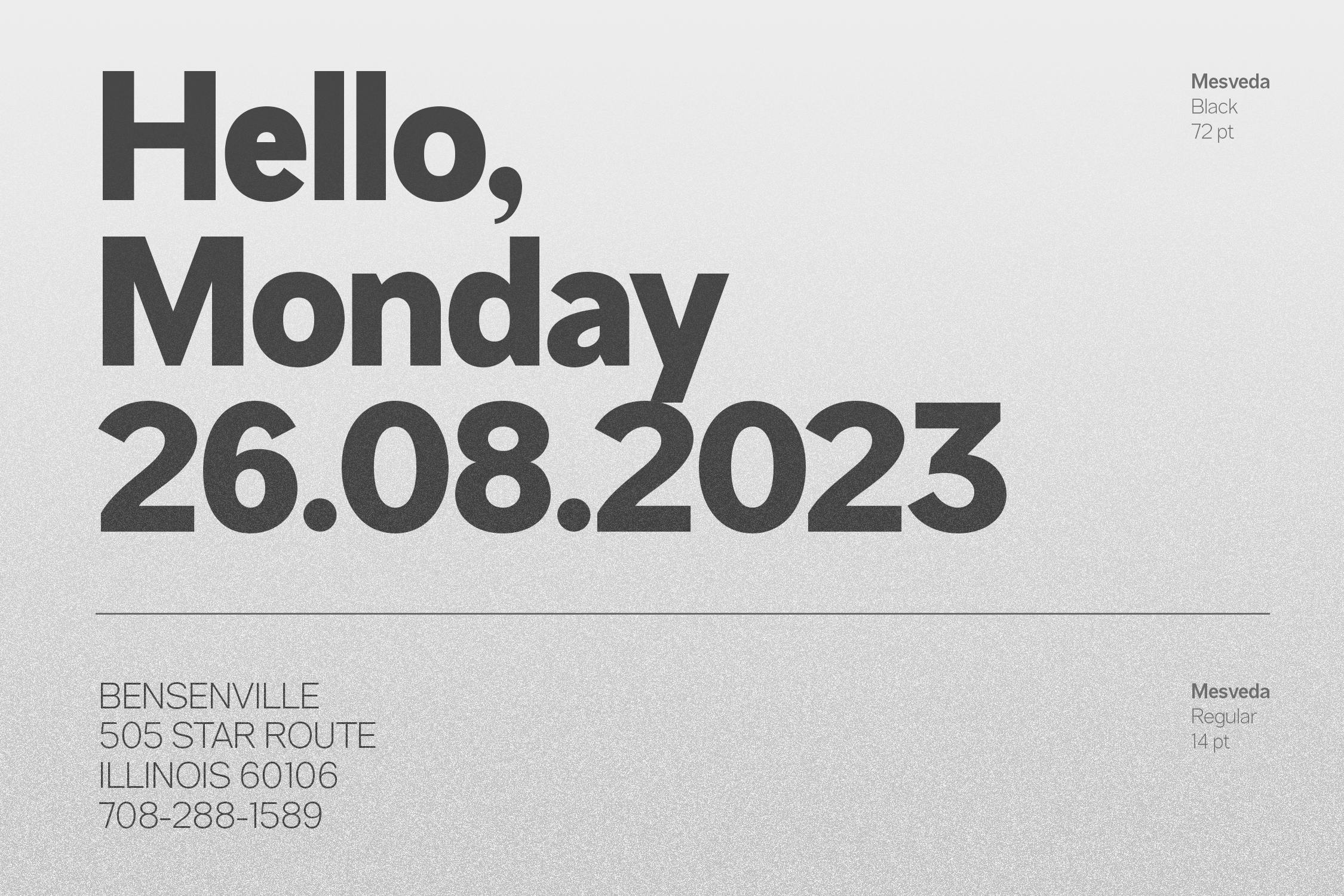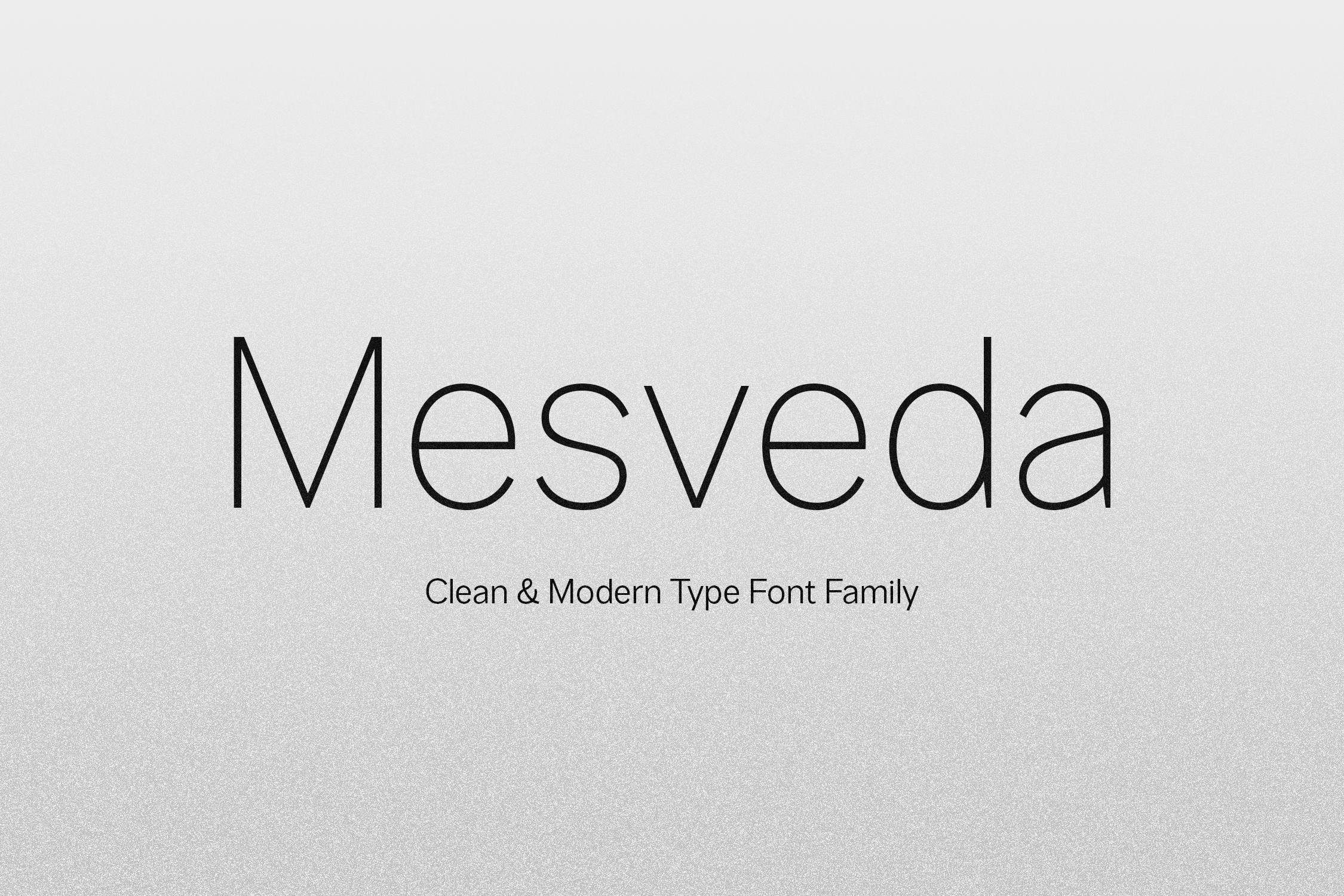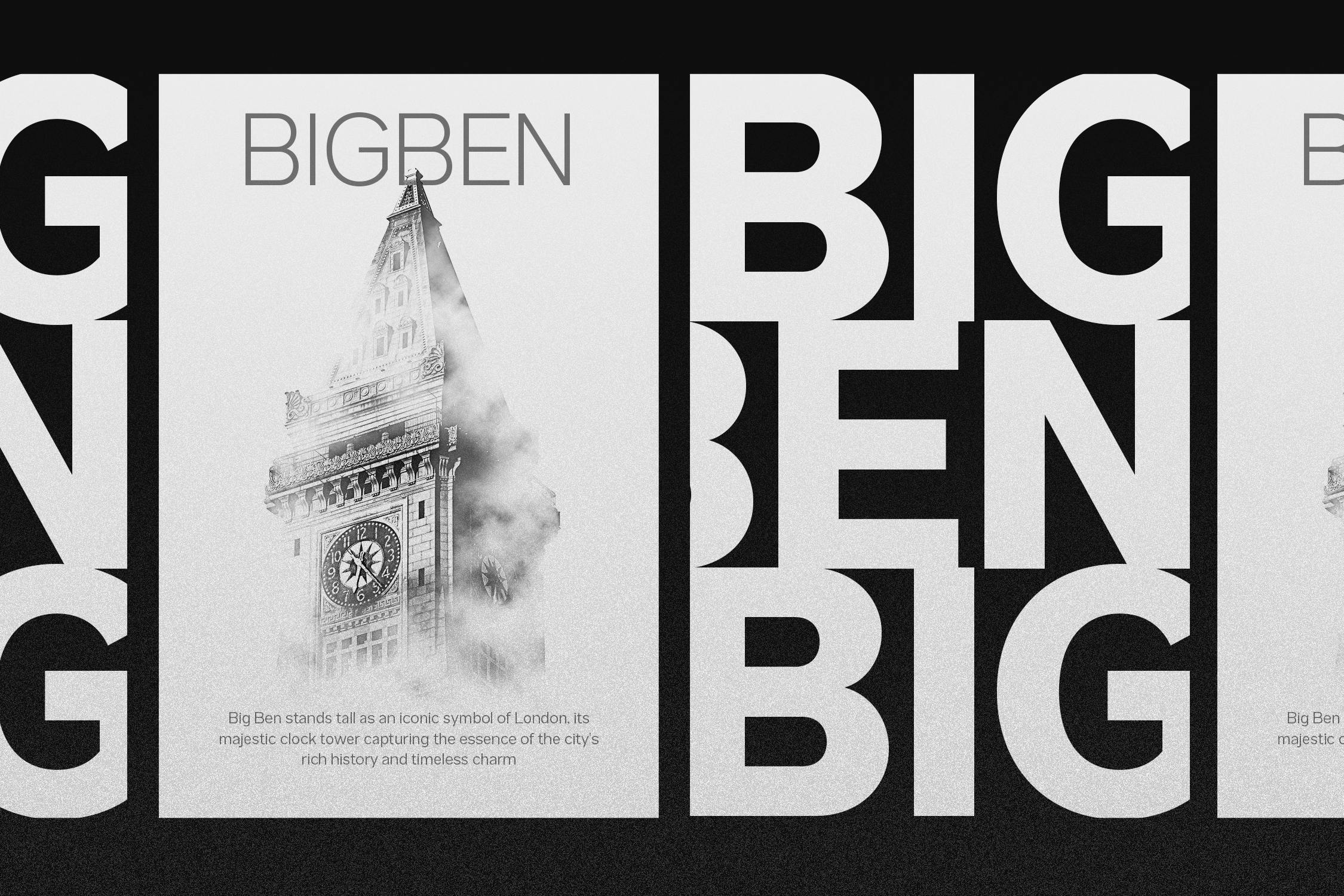
Mesveda Clean Modern Typeface Font
فونت Mesveda با طراحی مدرن و مینیمالیستی، مناسب برای پروژه‌های طراحی شما.
با افتخار ارائه می‌دهیم Mesveda - خانواده فونت سانس
Mesveda یک فونت مدرن و تمیز از نوع سانس است که به سادگی و زیبایی مینیمالیستی معروف است. این فونت در ۱۴ استایل مختلف از وزن‌های نازک تا بولد و شامل ایتالیک‌ها می‌باشد.
این فونت دارای حروف بزرگ و کوچک، اعداد و علائم نگارشی، پشتیبانی چند زبانه و ویژگی‌های اوپن‌تایپ است.
این فونت برای پروژه‌های طراحی شما از جمله طراحی وب، طراحی رابط کاربری، لوگوها، برندینگ، تبلیغات، طراحی محصولات، لوازم‌التحریر، طراحی مجلات، طراحی جلد کتاب و عناوین، عکاسی، نقل‌قول‌های هنری، طراحی‌های عروسی، طراحی‌های مد، رویدادهای خاص، برچسب‌ها، بسته‌بندی محصولات و غیره مناسب است.